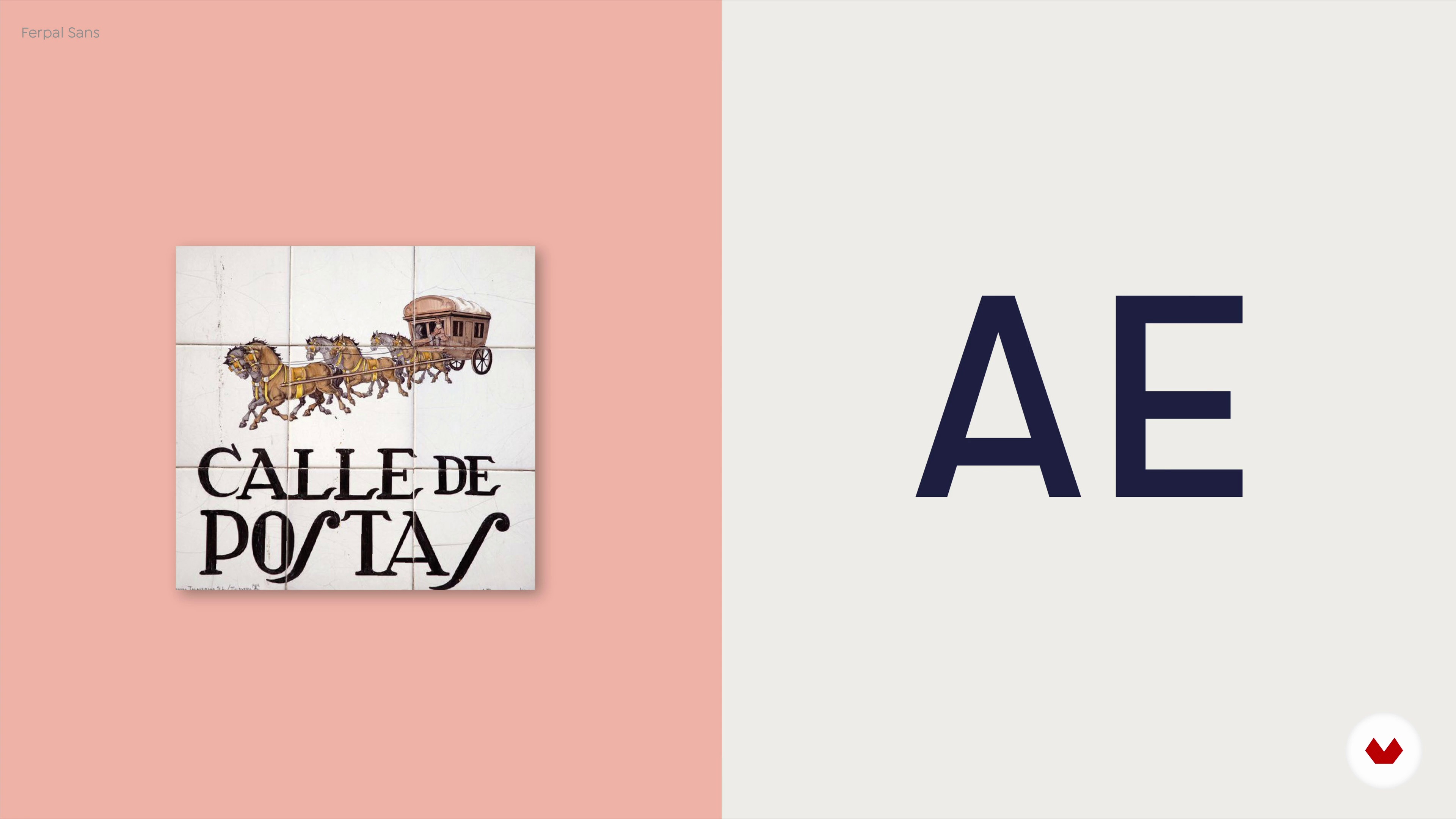
“Dans cette leçon, j'expliquerai ce qu'est la police de caractères et nous verrons quelques-uns des types les plus courants. De plus, nous jouerons avec les mots et ferons une formation à l'aide de la typographie.”
Dans cette leçon, Silvia Ferpal aborde le sujet : Types de types, qui fait partie du cours Domestika en ligne : Initiation au graphisme. Découvrez les fondamentaux du graphisme et mettez en forme vos idées en jouant avec les images, la typographie, la couleur et la composition.
“Maintenant que tu sais créer des images pour représenter un concept. il est temps de le compléter typographie. Pour beaucoup. la typographie est la partie la plus ennuyeuse du design. cependant. elle est essentielle et c'est le principal. presque autant que l'image. D'ailleurs. il y a beaucoup de designers qui utilisent la typographie comme Désolé. je ne t'ai pas expliqué ce que c'est. La typographie se réfère à cette méthode d'impression autrefois avec des caractères en plomb ou en bois. Les caractères sont ces petites lettres utilisées pour imprimer. Cependant. la réalité est qu'aujourd'h...”